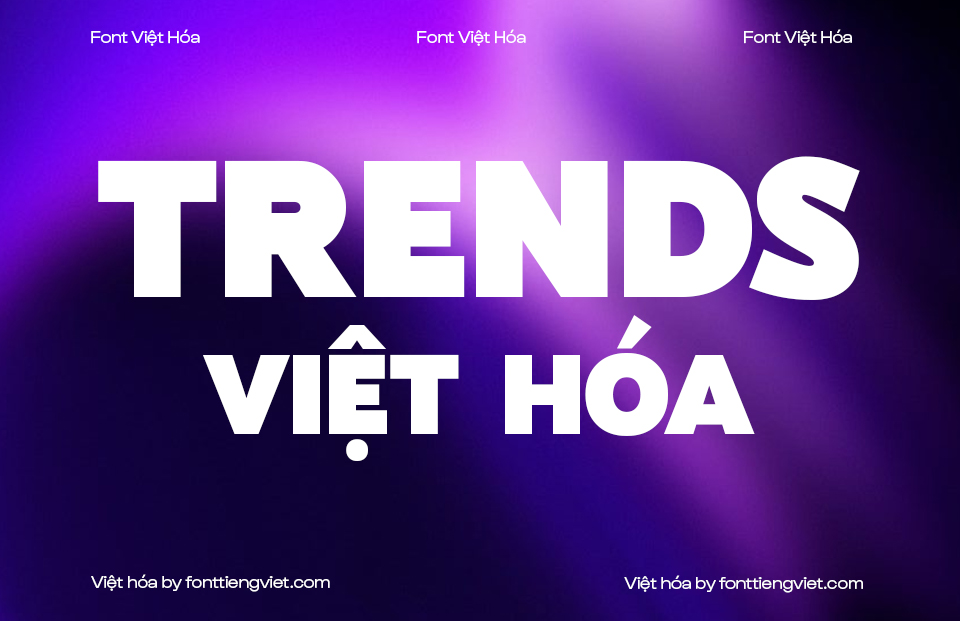
Font Việt hóa 1FTV VIP Trends
Trong thế giới thiết kế đồ họa hiện đại, việc lựa chọn một bộ phông chữ phù hợp không chỉ giúp truyền tải thông điệp mà còn khẳng định phong cách riêng biệt của tác giả. Font Việt hóa 1FTV VIP Trends đang trở thành tâm điểm chú ý của cộng đồng sáng tạo tại Việt Nam nhờ vẻ đẹp tinh tế và tính ứng dụng cao. Nếu bạn đang tìm kiếm một Font Miễn Phí để nâng cấp các sản phẩm thiết kế của mình, thì đây chính là bộ sưu tập không thể bỏ qua. Bài viết này sẽ giúp bạn hiểu rõ lý do vì sao bộ font này lại được ưu ái đến vậy trong các xu hướng thiết kế mới nhất hiện nay.
Lý do Font Việt hóa 1FTV VIP Trends dẫn đầu xu hướng thiết kế
Bộ Font Việt hóa 1FTV VIP Trends không chỉ đơn thuần là các ký tự văn bản mà còn là sự kết hợp hoàn hảo giữa tính thẩm mỹ và kỹ thuật Việt hóa chỉn chu. Điều này giúp các nhà thiết kế loại bỏ hoàn toàn nỗi lo lỗi font hoặc thiếu dấu khi gõ tiếng Việt, một vấn đề thường gặp ở các bộ phông chữ quốc tế.
Đặc điểm nổi bật của bộ font 1FTV VIP Trends
Đặc điểm nhận diện rõ nét nhất của Font Việt hóa 1FTV VIP Trends chính là sự đa dạng trong các đường nét. Từ những nét chữ thanh mảnh, sang trọng dành cho các thiệp mời cao cấp đến những nét đậm, mạnh mẽ cho các banner quảng cáo, bộ font này đáp ứng mọi nhu cầu khắt khe nhất. Các ký tự được tinh chỉnh khoảng cách hợp lý, giúp văn bản trở nên dễ đọc và có nhịp điệu hơn trên mọi nền tảng hiển thị. Đặc biệt, bảng mã Unicode chuẩn giúp font tương thích tốt với hầu hết các phần mềm thiết kế như Photoshop, Illustrator hay Canva.
Ứng dụng thực tế trong công việc sáng tạo
Nhờ tính linh hoạt vượt trội, Font Việt hóa 1FTV VIP Trends được ứng dụng rộng rãi trong nhiều lĩnh vực khác nhau. Trong ngành quảng cáo, nó thường xuất hiện trên các poster phim, bìa tạp chí hoặc hình ảnh truyền thông trên mạng xã hội. Đối với các bạn học sinh và sinh viên, bộ font này là công cụ đắc lực để trang trí bài thuyết trình hoặc làm báo tường, giúp nội dung trở nên sinh động và chuyên nghiệp hơn. Sự hiện diện của nó giúp tạo nên một tổng thể hài hòa, bắt mắt và dễ dàng thu hút sự chú ý của người xem ngay từ cái nhìn đầu tiên.
Lưu ý khi phối hợp font chữ trong thiết kế
Một quy tắc vàng khi sử dụng Font Việt hóa 1FTV VIP Trends là không nên lạm dụng quá nhiều kiểu chữ trong cùng một sản phẩm. Bạn nên kết hợp bộ font này với một font không chân (Sans-serif) đơn giản để cân bằng thị giác. Việc tạo ra các khoảng trắng hợp lý xung quanh chữ cũng giúp bộ font phát huy tối đa vẻ đẹp sang trọng vốn có của nó.
Kết luận về bộ sưu tập font chữ đỉnh cao